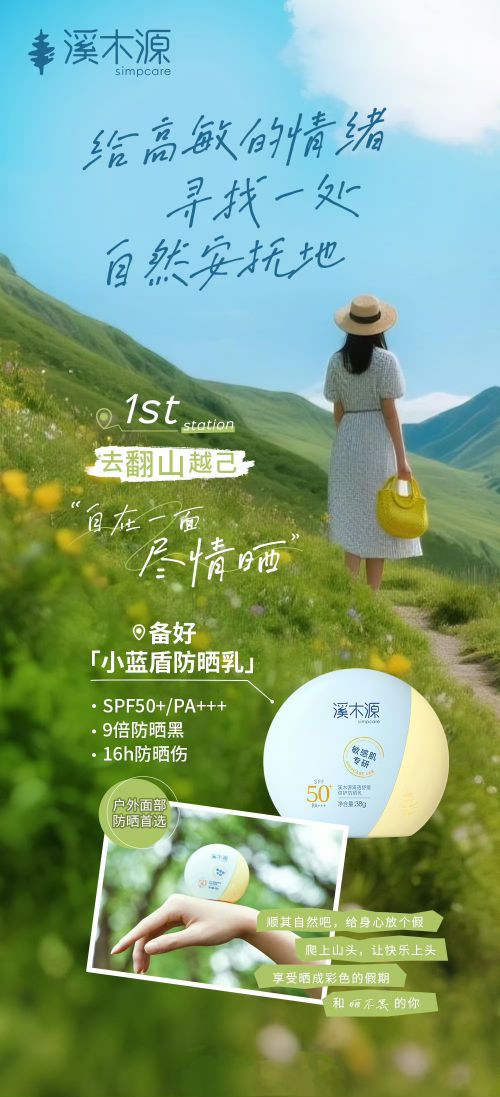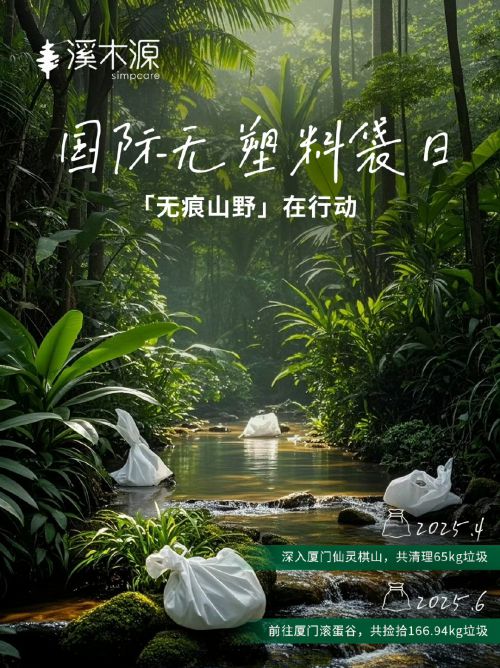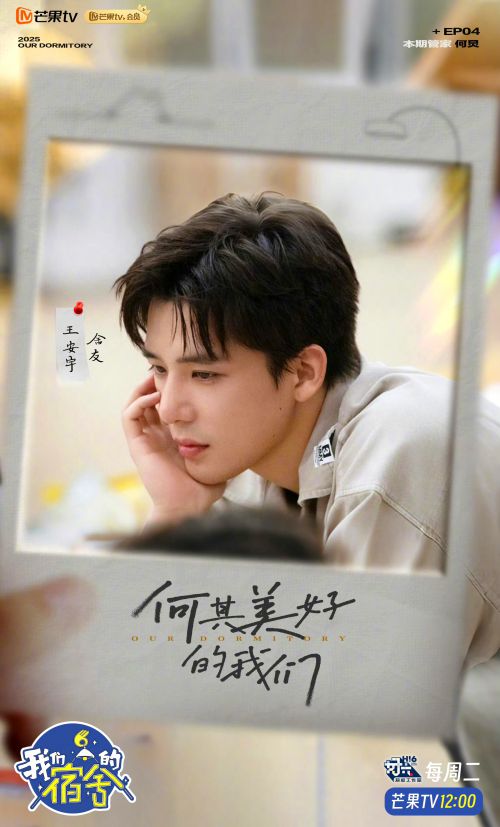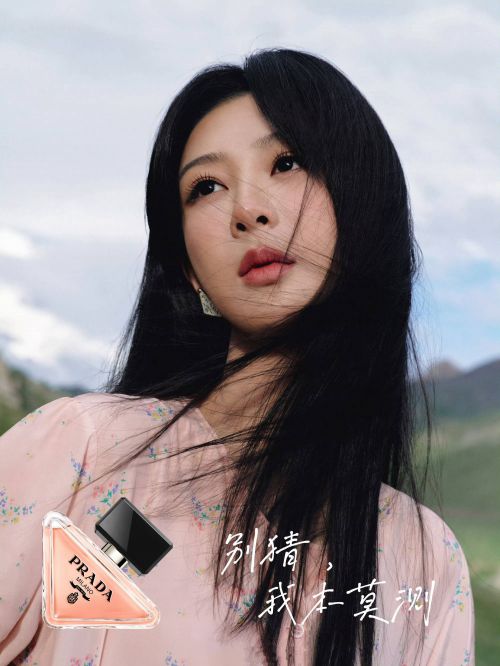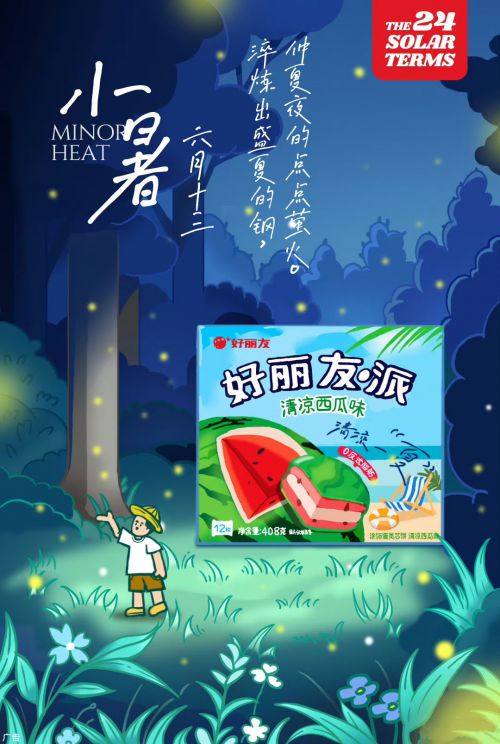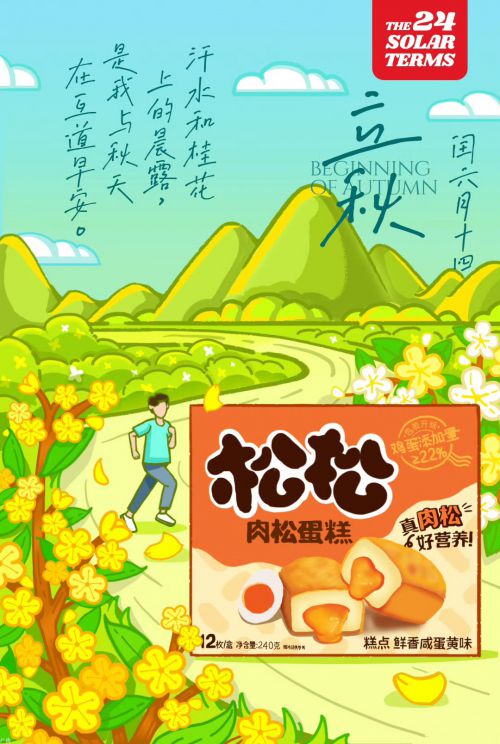
默陌专辑手写体
默陌专辑手写体是一款自由清新的硬笔手写体,默陌专辑手写体字形纤长舒张,笔画均匀圆润,整体呈左倾之势,轻盈灵动,洋溢着青春的气息。
默陌
默陌是一名独立设计师,从事字体创意设计多年,目前已发布默陌水墨手迹系列、默陌硬笔手写体系列、默陌奇趣可爱手写系列等30余款字体字库作品,广泛应用于平媒、影视、手机端显示等场景。默陌字体字形多变,风格多元,坚持致力于传统书法意趣和现代手写个性的有机融合,创作出更多美好的原创手迹。